タイポグラフィ60の視点と思考
パイ インターナショナルは2024年12月20日に、タイポグラフィのエキスパート集団〈日本タイポグラフィ協会〉のクリエイター60人がそれぞれの専門領域と豊富な経験から語るデザインの思考と手法をカテゴリーを60に細分化し、制作ポイントを作品事例とともに解説『タイポグラフィ60の視点と思考』を発売した。
タイポグラフィのエキスパート集団〈日本タイポグラフィ協会〉のクリエイター60人がそれぞれの専門領域と豊富な経験から語るデザインの思考と手法をカテゴリーを60に細分化し、制作ポイントを作品事例とともに解説。
デザインの可能性を広げ、バイブルとなる必携の1冊となる。(協会設立60年記念書籍)
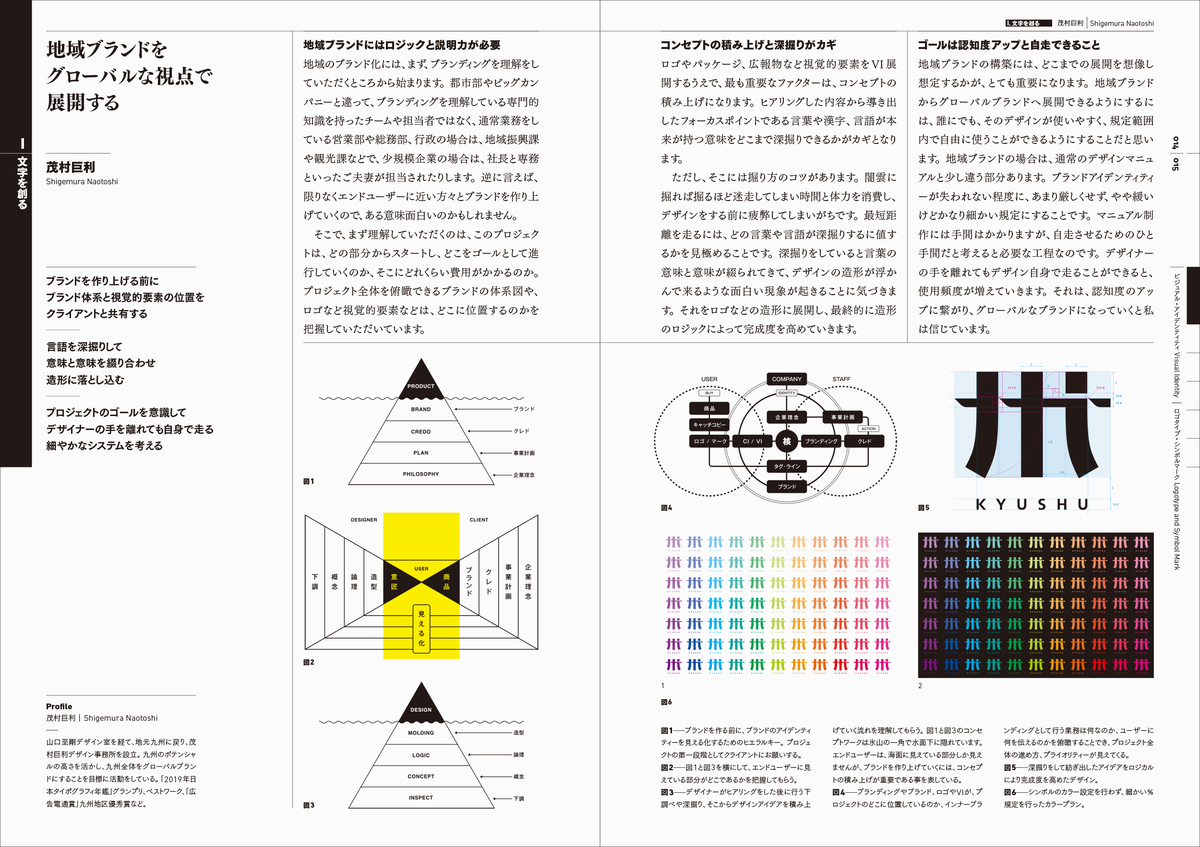
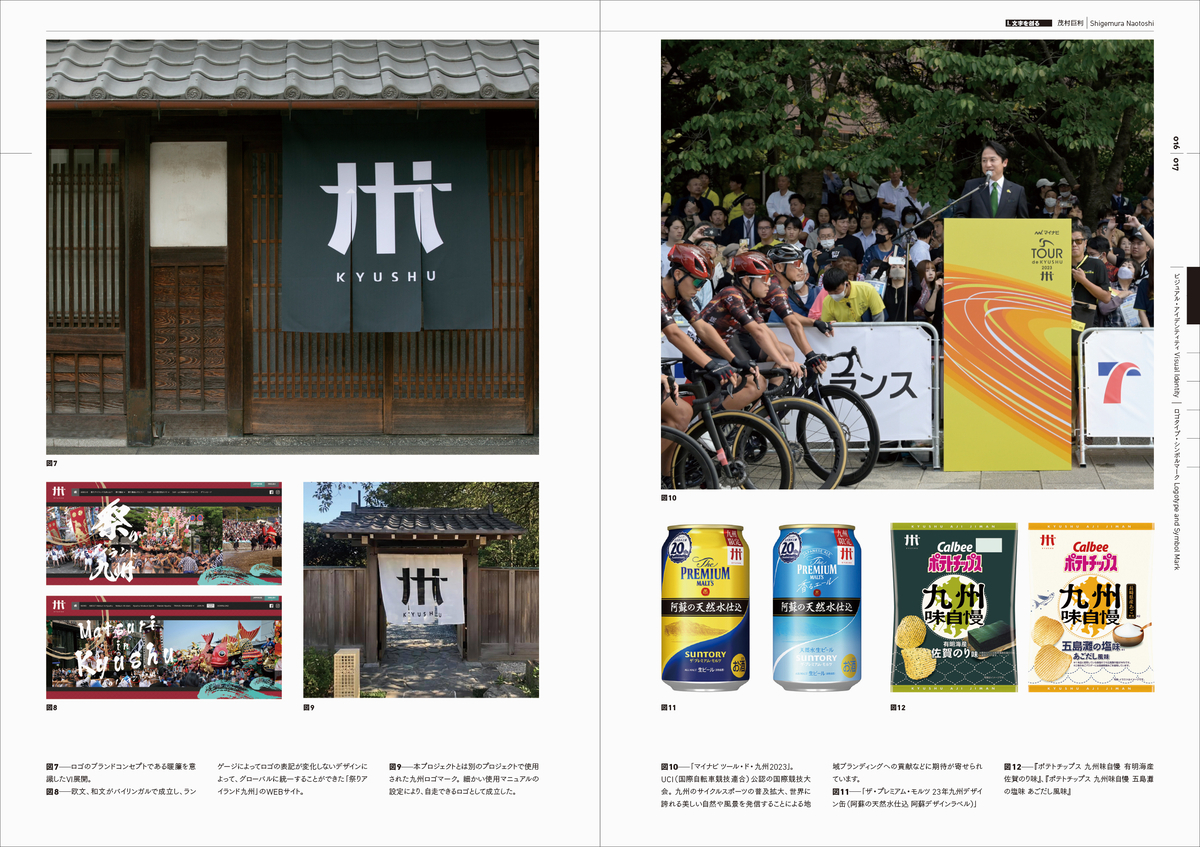
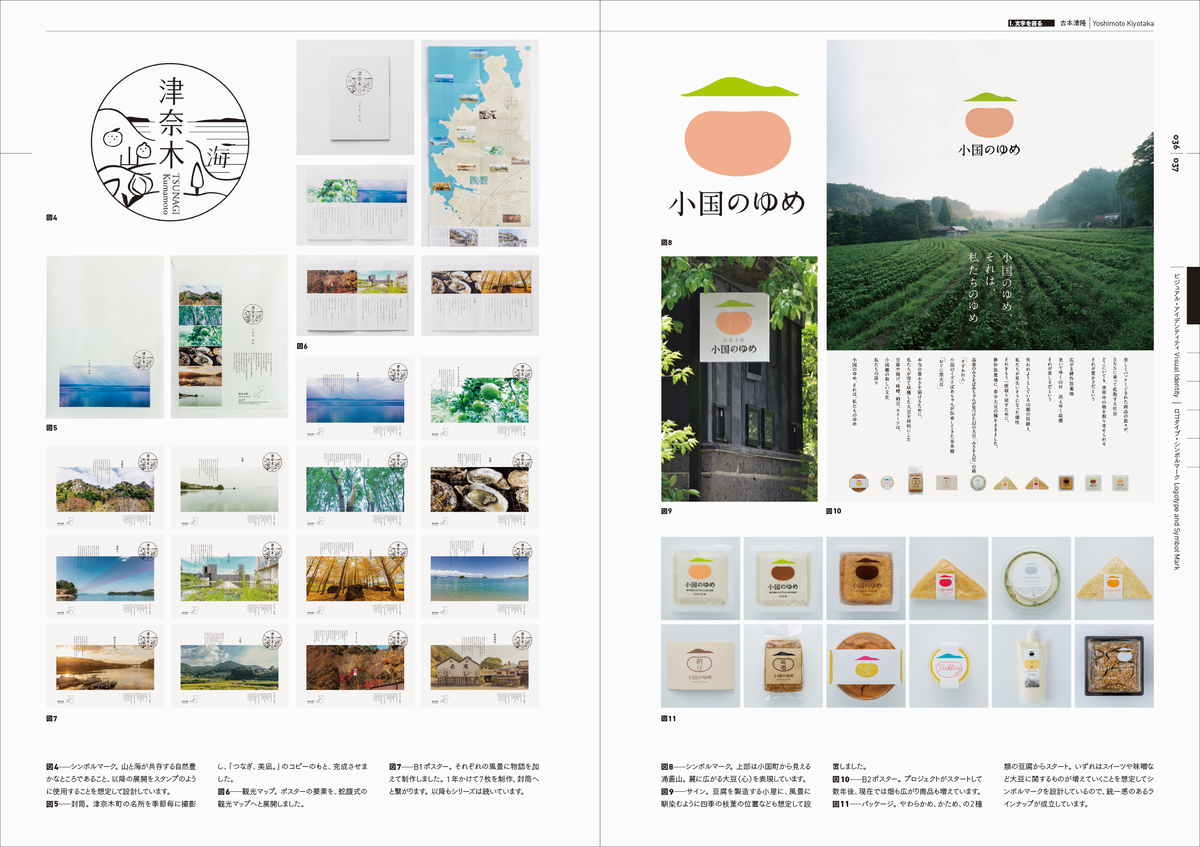
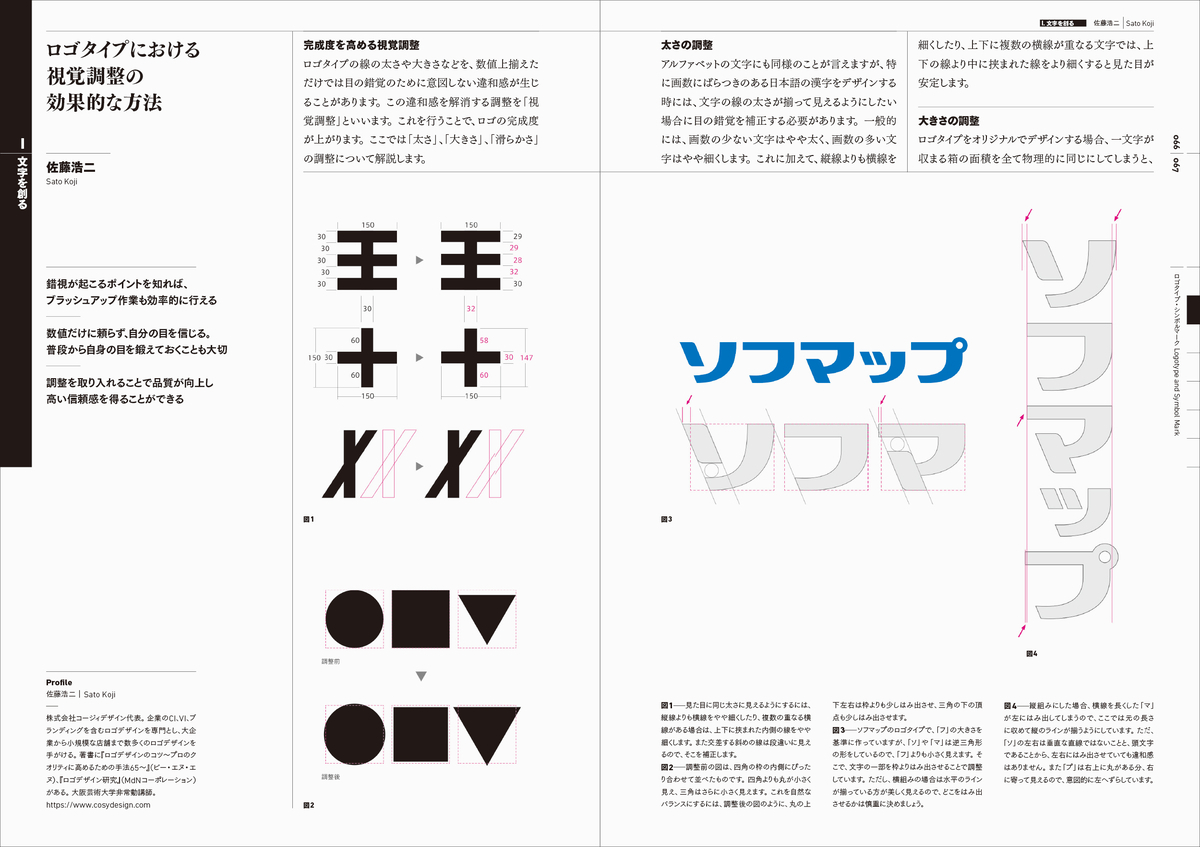
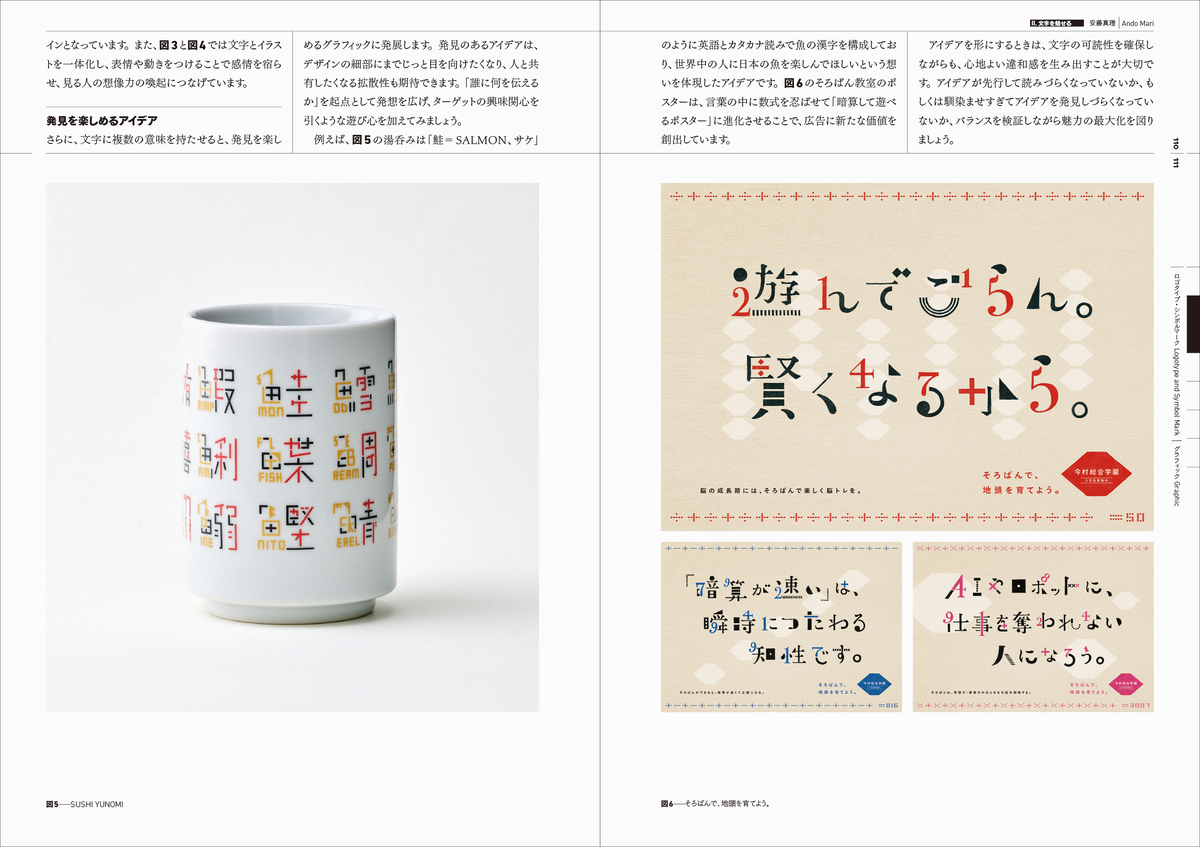
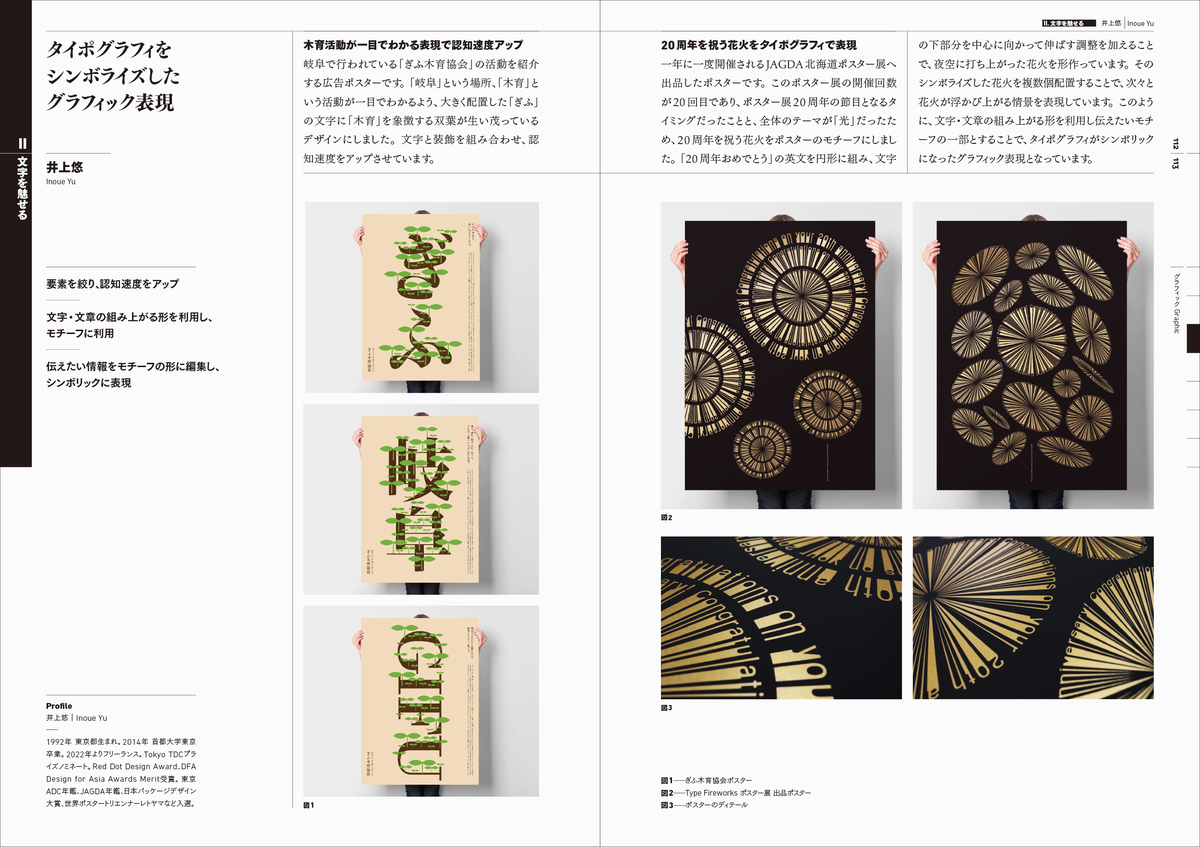
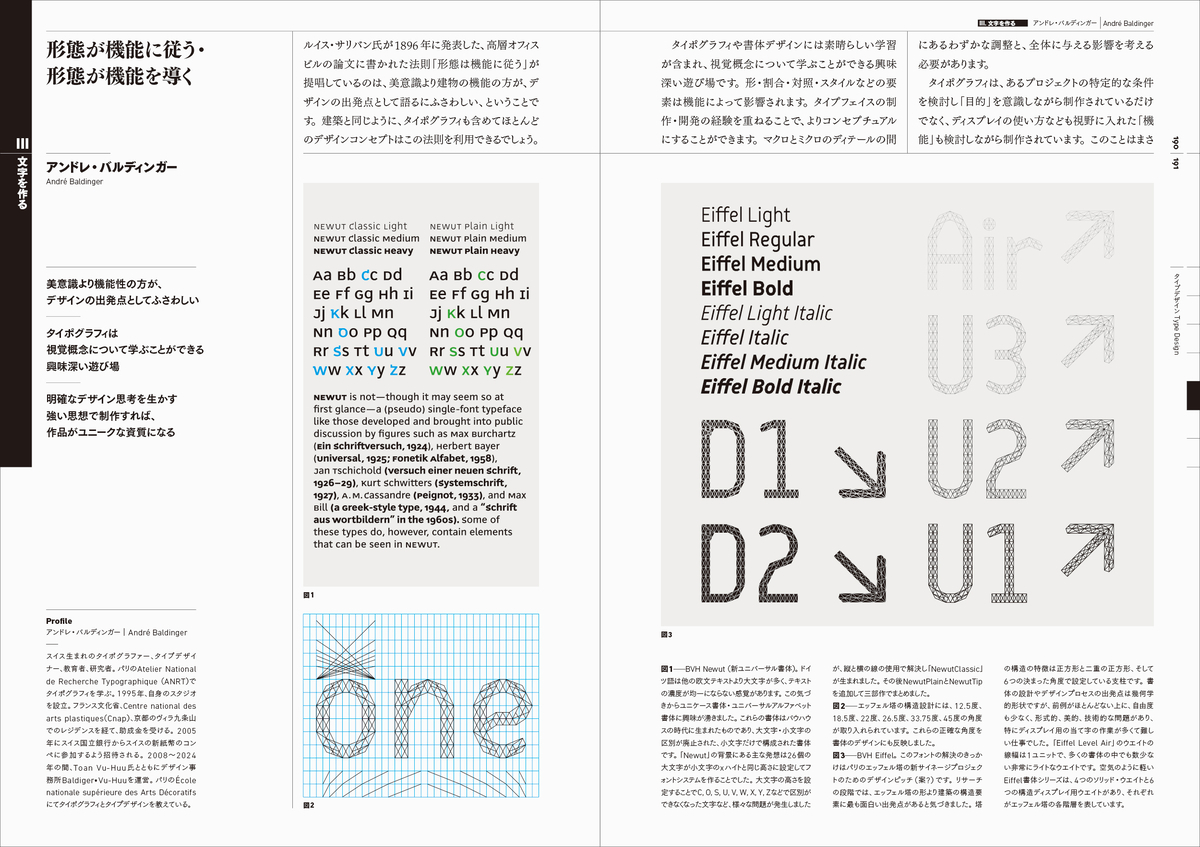
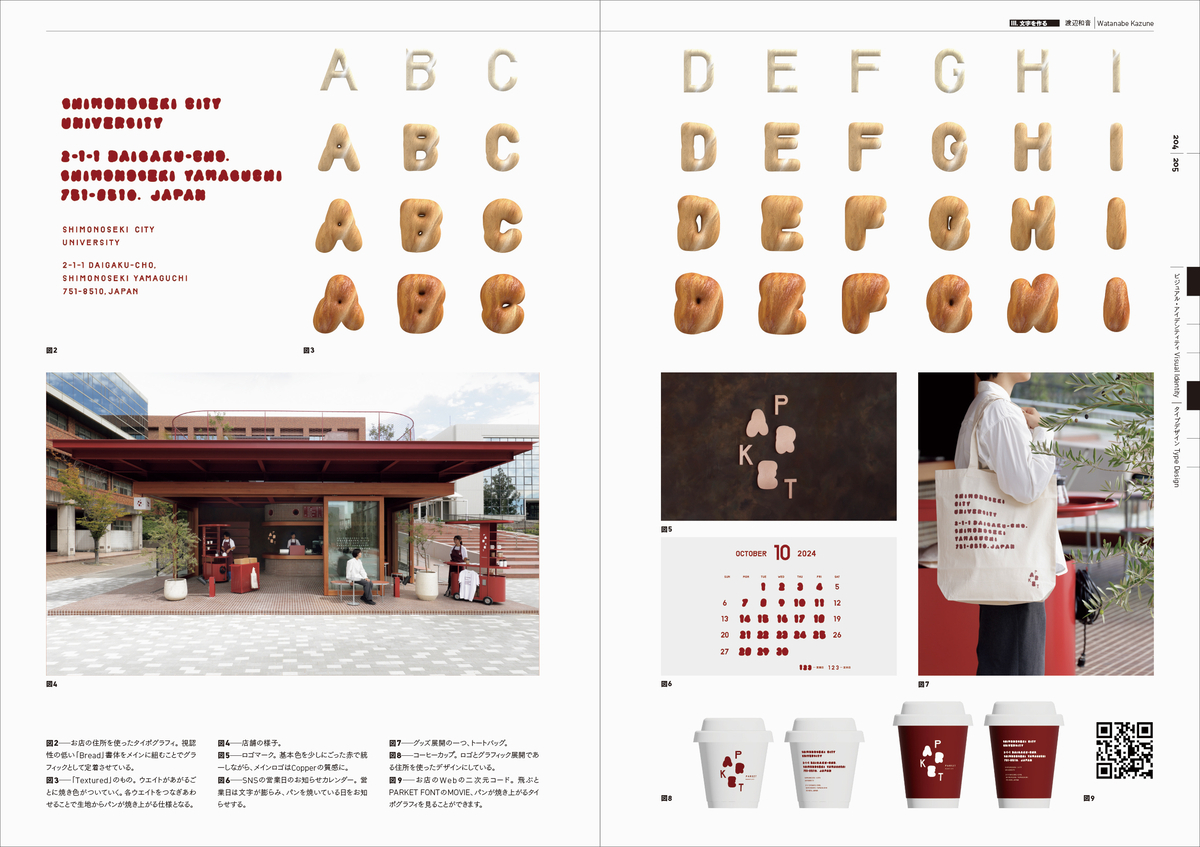
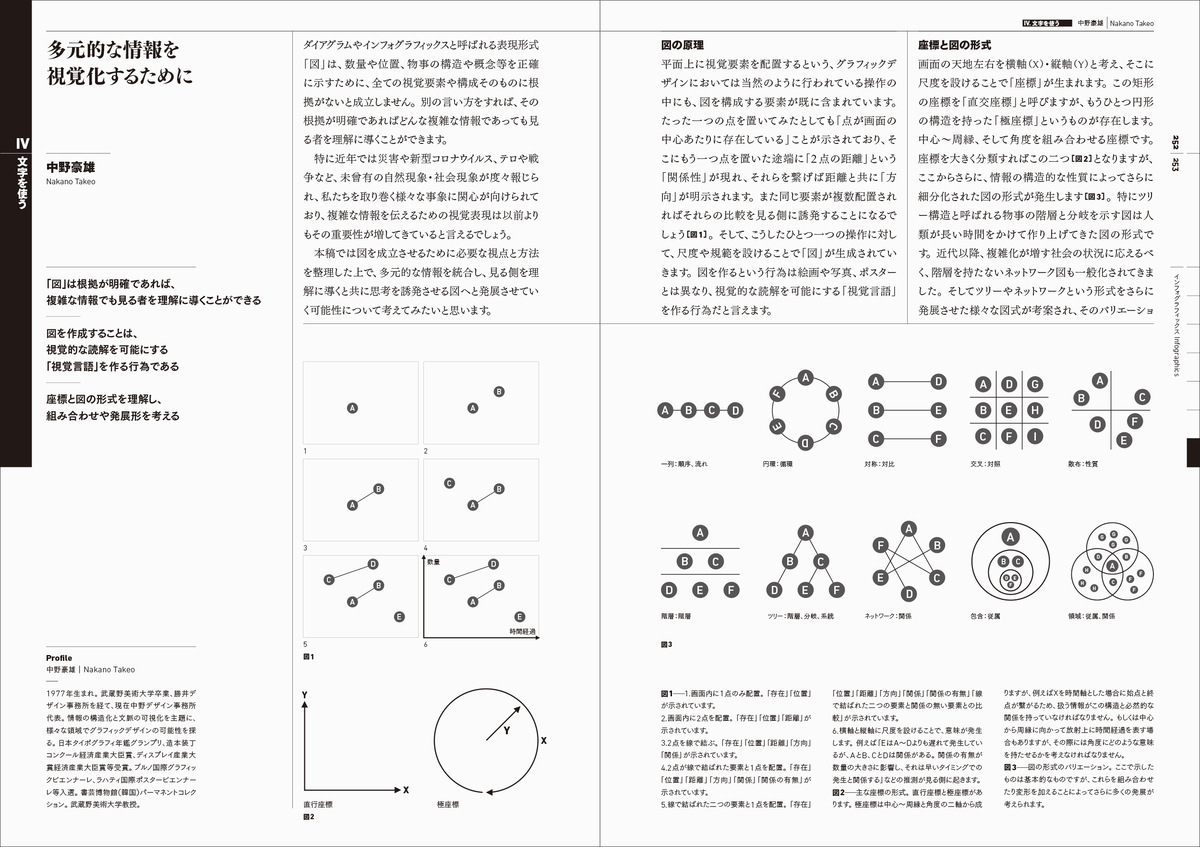
タイポグラフィという言葉は、文字及び文字を利用したデザインとして現在は幅広く使われています。その成り立ちを遡れば、活字が主要な印刷技術であった時代の活字組版職人をタイポグラファーと言っていたことに始まります。それは活字という情報を伝えるためのパーツから、その組み方、いわゆる見せ方による付加価値が、情報をただ伝えるだけではなく、伝え方の質や方法が重要であるということの発見だったのでしょう。それからメディアは目まぐるしい発展を遂げたのですが、文字そのものが変わったわけではありません。ただ、手書きに始まり、活字、写植、デジタルフォントへと技術が変化していく中での明らかな違いは、文字のフォルムのデザインはもとより、その変形や詰め方など文字の組み方のデザインの表現の自由度が圧倒的に広がったということです。それは文字が記号としての情報伝達の手段であるということに加えて、文字の佇まいが感覚的な多くの情報を含む可能性の広がりでもあります。かくしてデザイナーは、とりわけ文字のデザインに携わるデザイナーは、その視覚的な機能性や表現手法のクオリティを追求することに心血を注いできました。とは言え、その目的も立場もそれぞれ違うデザイナーたちにとって、その評価基準は一様ではありません。最も理想的なタイポグラフィというものがあるわけではなく、そこに多くの理想的な答えが存在する多様性が認められることは当然なのです。では、若きデザイナーたちは何を指針として学べばいいのでしょう。それは多くの視点、多くの思考からその可能性の広さを学ぶことだと考えます。そういったことから本書を企画しました。タイポグラフィデザインを研究、実践するデザイナーたちが集まった団体である、日本タイポグラフィ協会のメンバー60 人が、それぞれの立場やそれぞれの経験から生まれた、それぞれのデザイン手法を語ります。まさに60の多角的視点がここにあります。奇しくも協会は今設立60 年の節目を迎えます。これからますます広がっていくであろうタイポグラフィの世界に向けて、本書がそれを学ぶ若きデザイナーたちの助けになれば幸いです。
『タイポグラフィ60の視点と思考』コンテンツ
文字を創る
小川明生/茂村巨利/武井衛/トモクサユウタ/ハン ヒソク/細谷百代/??本清隆/石原利貴/伊勢田雄介/入山隆一朗/大庭三紀/加保美咲/桑山一弥/坂口拓/佐藤浩二/高田雄吉/高橋善丸/竹内紀子/永井弘人/野宮謙吾/洪 衛/八十島博明
文字を魅せる
粟辻美早/小玉文/安藤真理/井上悠/オガワヨウヘイ/小川航司/笠井則幸/白瀧真之/杉崎真之助/仙石吉德/登坂昭夫/冨貫功一/平山政根/本多り子/森相文宏/峠田充謙
文字を作る
片岡朗/葛本京子/加藤雅士/神田友美/木龍歩美/田中裕子/アンドレ・バルディンガー/閻?/余秋子/渡辺和音/汪宣丞
文字を使う
藤本孝明/阿部宏史/リトウリンダ/アオキジュニヤ/コントヨコ/舟山貴士/ブラザトン ダンカン/保田卓也/寺島隆介/中島安貴輝/中野豪雄